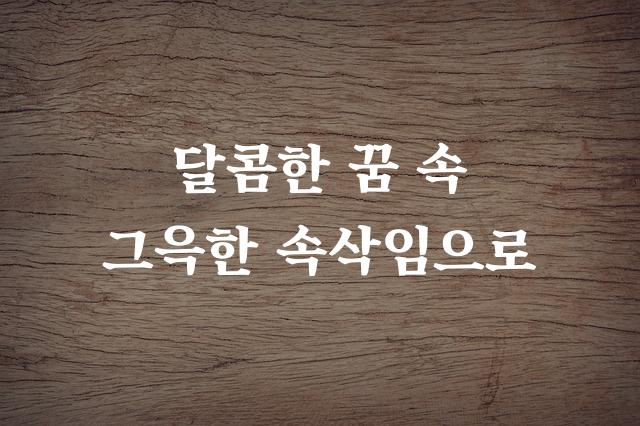
부여군 지역공동체 활성화 재단에서 제작한 '신동엽 손글씨'는 진정성 있는 캘리그라피 스타일의 폰트입니다. 삐뚤빼뚤한 특징이 감성적인 터치를 더해 주며, 손으로 직접 쓴 듯한 느낌을 선사합니다.
신동엽 손글씨은(는)
손글씨, 펜/붓터치, 감성적인 계열의 생김새를 가지고 있으며
초대장, 인사말 카드, 일기/편지 등에서 자주 활용되며, 효과적인 메시지 전달에 적합합니다.
이 폰트는 크리에이티브, 문화/예술, 엔터테인먼트 분야에 잘 어울리며,
따뜻한, 감성적인, 편안한 느낌을 담고 있는 것이 특징입니다.